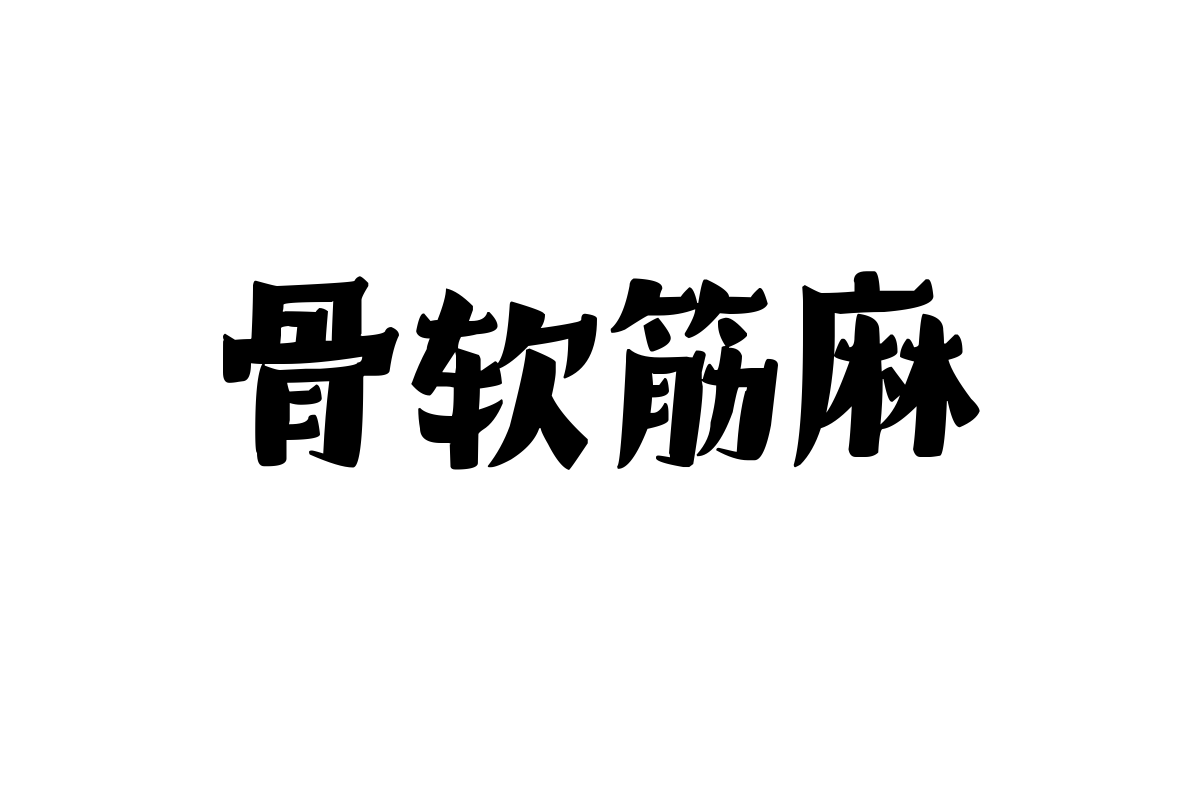
妙淘体是由北京造字工房文化传播有限公司设计的一款字体。这款字体具有独特的设计风格,笔画流畅自然,线条粗细均匀,结构紧凑,整体给人一种简洁明了的感觉。
妙淘体的字形结构严谨,每个笔画都经过精心设计,使得整个字体看起来既有力度又不失美感。它的笔画粗细变化丰富,既有粗犷的线条,又有精细的小细节,使得字体在视觉上具有很强的吸引力。
妙淘体的排版效果也非常出色,无论是在海报、广告还是其他设计作品中,都能展现出其独特的魅力。它不仅能够提升作品的整体视觉效果,还能增加文字的可读性,使读者更容易理解和接受信息。